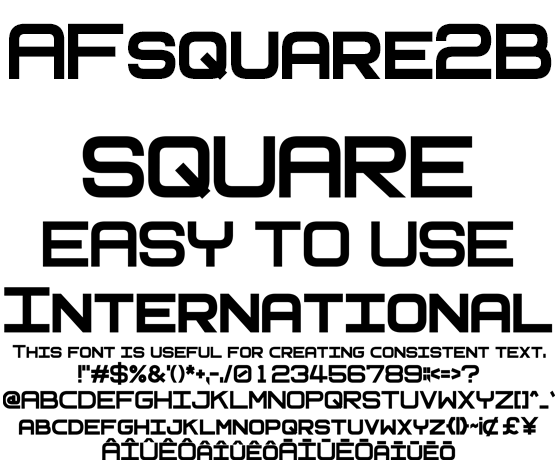
四角ボディな欧文 AFsquare2B
AFsquare2B
個々字形の特徴に左右されず正方形な縦横サイズで作られた等幅欧文フォントです。流れるようなデザインはモダンな表現に最適です。太字のボールドで強調されたワードは、動画のエンドロール、テロップ、液晶表示器、操作パネル、メニューなど幅を統一させたい場所にご利用ください。